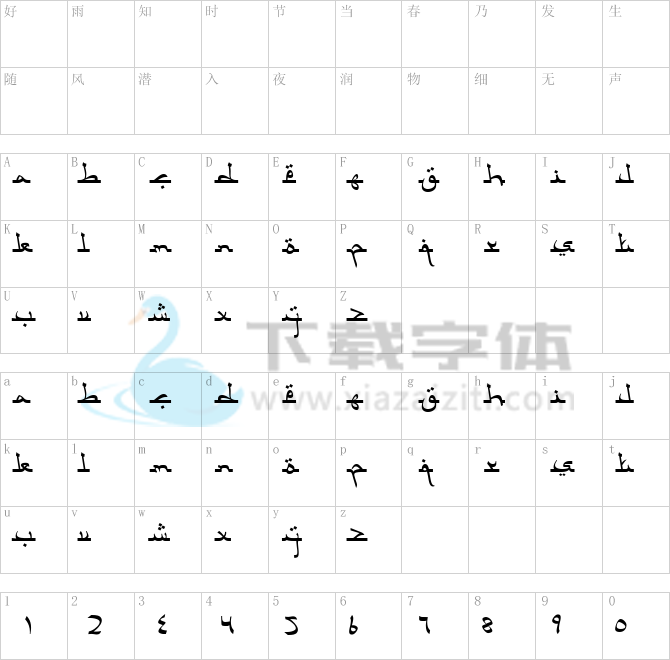
Aceh Darusalam.ttf字体下载,这款字体结构工整、笔画清晰,兼顾美观与易读性,适用于标题、正文、海报、包装、LOGO 等多种场景。字形优雅稳定,风格百搭耐看,适配日常排版与创意设计,让文字呈现更舒适、更具质感。Aceh Darusalam.ttf字体下载一笔一画,皆是细节,以均衡的比例、流畅的线条打造舒适视觉体验,字形端正大气,风格简约现代。无论是商业设计、品牌宣传还是日常排版,都能轻松驾驭,让文字更有格调与力量。Aceh Darusalam.ttf字体下载字体下载。